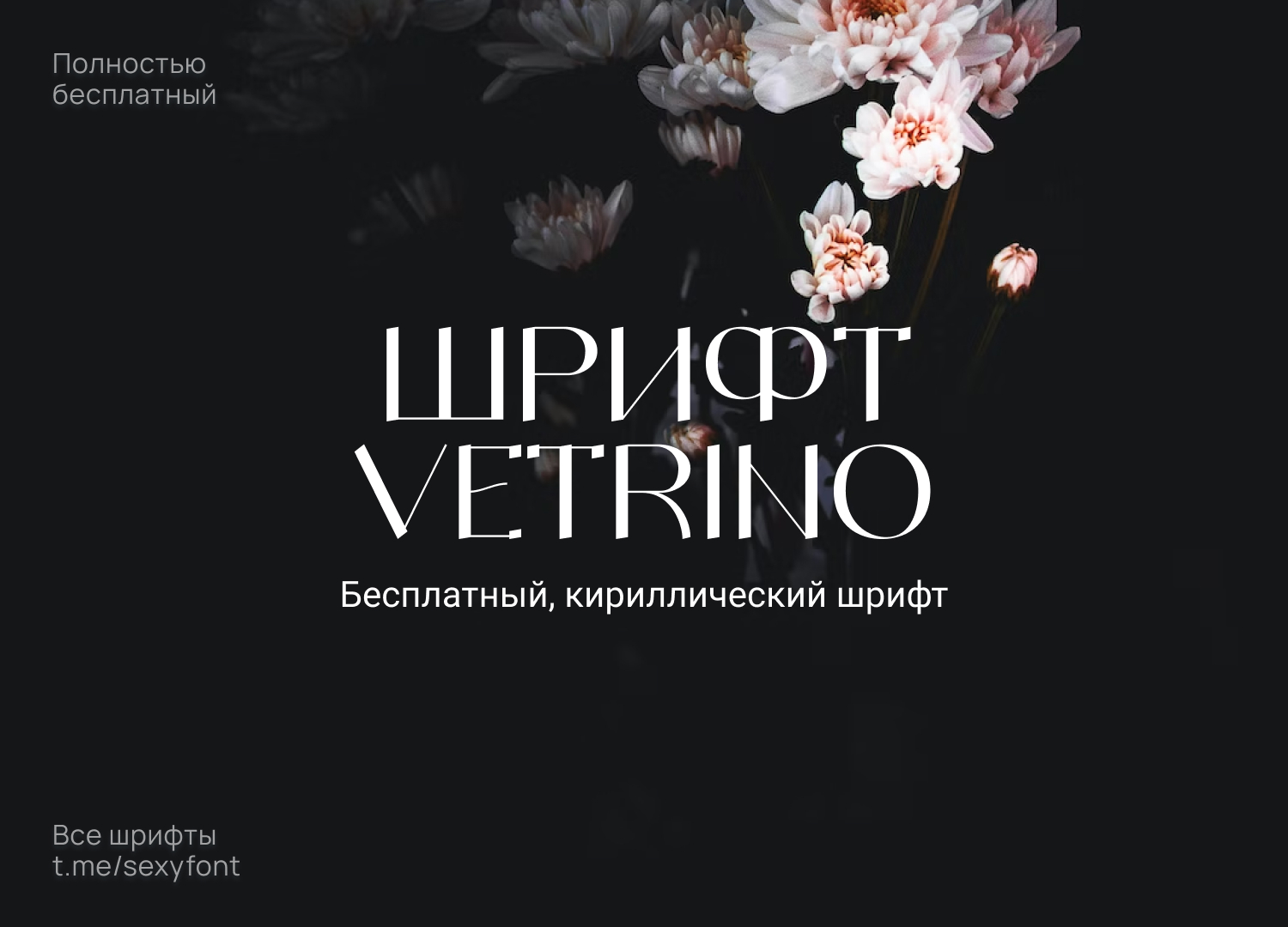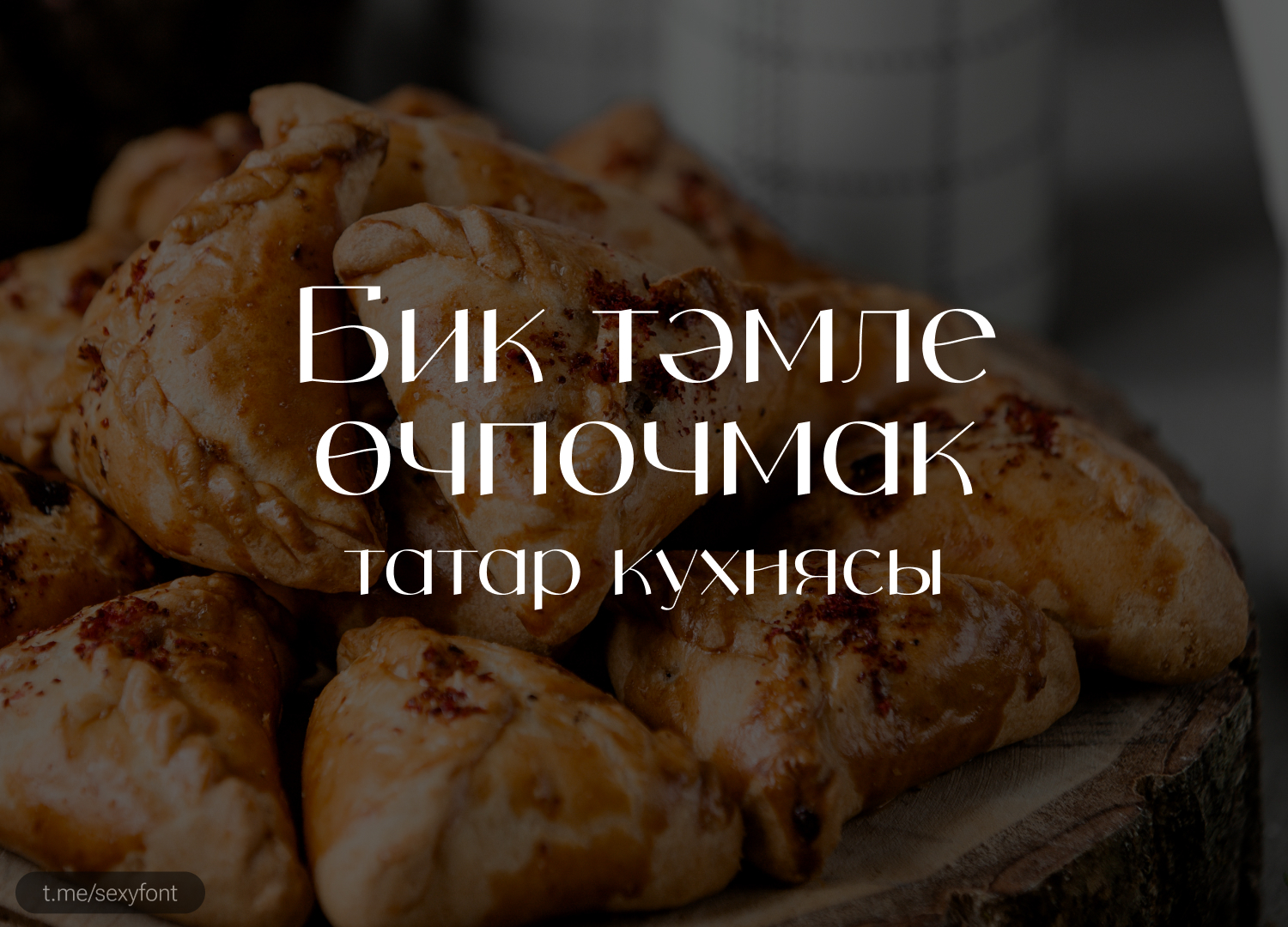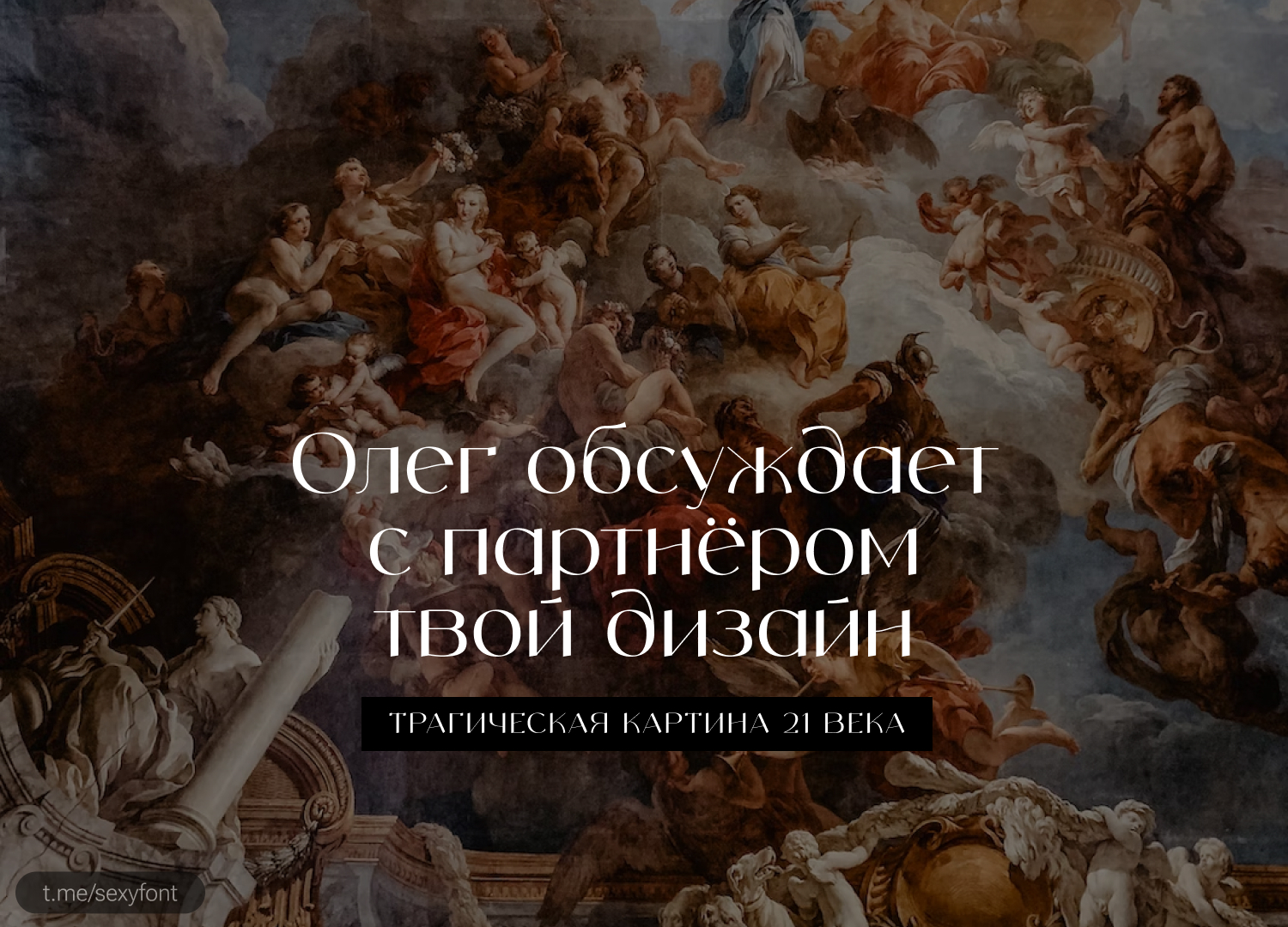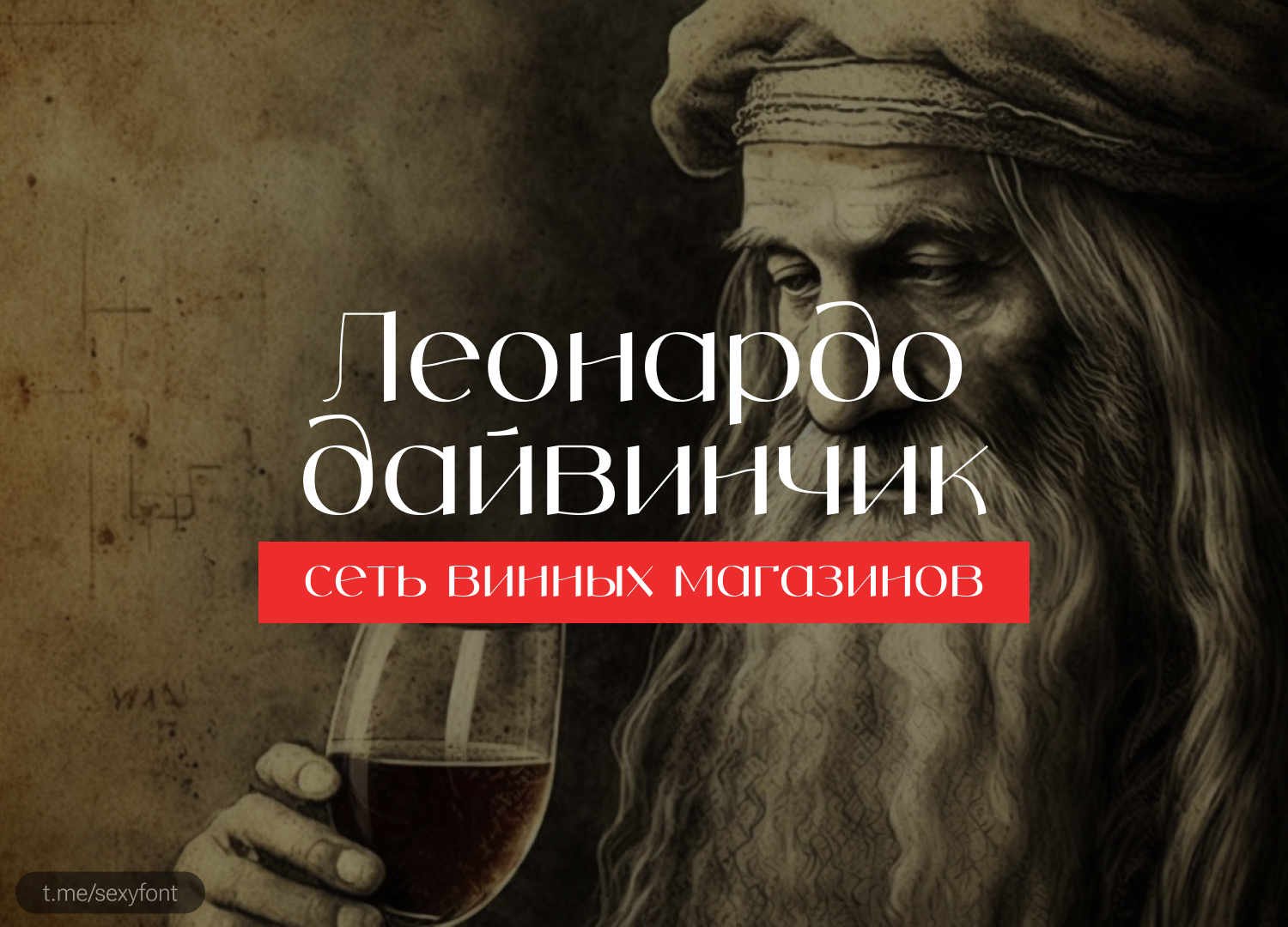
Кириллический шрифт Vetrino
Шрифт Vetrino. Кириллический шрифт с засечками. Поддерживает татарские символы) Такое не супер часто встречается. Начертание бесплатно для личного и коммерции.